除了口味,我们还记住了包装上的字!
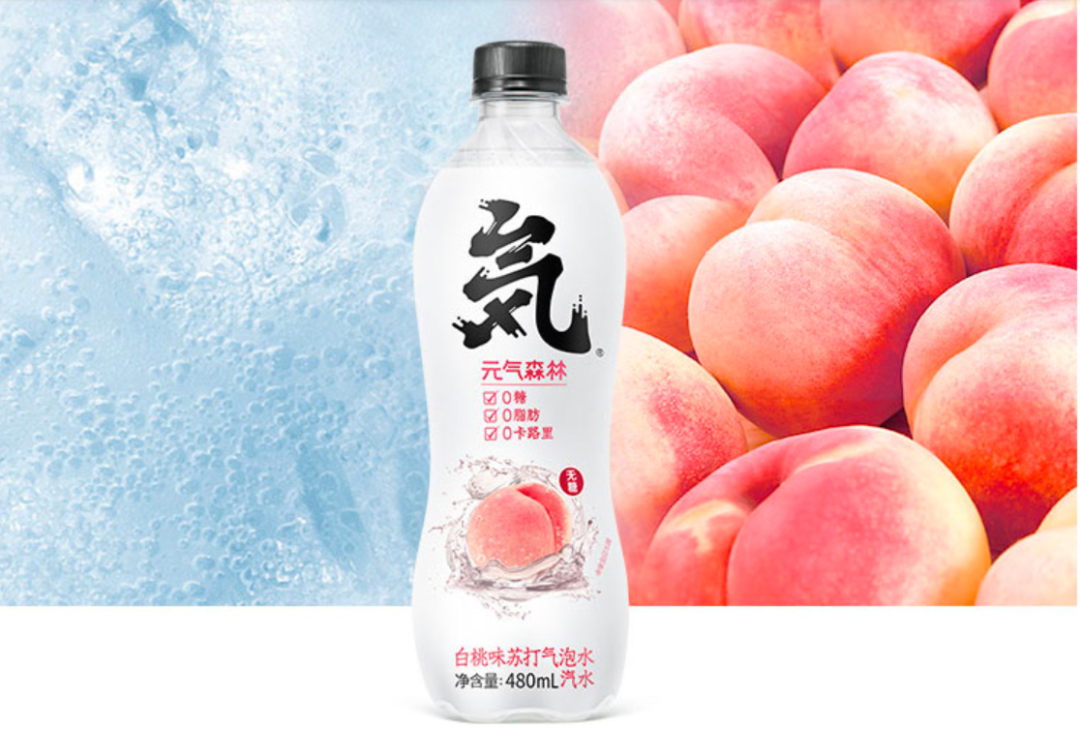
元气森林包装上凸显了“気”字
提到元气森林,你可能记不得包装图案的细节,但一定记得住“气”下面的“×”;提到可口可乐,它飘逸的花体“Coca Cola”或“可口可乐”字体一定给你留下深刻印象。这些产品的字体设计作为包装的一部分,除了审美价值,也成为品牌商业资产的一部分。
一个经典、爆款产品想给消费者留下深刻印象,除了“你爱我我爱你,蜜雪冰城甜蜜蜜”的广告旋律洗脑、除了明星爱豆的代言助力,为什么包装字体这个经常被忽略的元素也很重要?如何打造产品包装的“爆款高分字体”?合适的字体能为品牌会让食品/饮料看起来更好吃/好喝吗?
FBIF2021食品饮料创新论坛创新包装分论坛上,屹涛创意设计创始人陈嵘对字体的解读让我们意识到字体对包装的意义。今天,我们再来聊一聊,食品包装字体的那些事儿。
源头:历史的沉淀赋予设计的沃土
汉字的演变史十分漫长,长到可以拍出一部纪录片。从最早的甲骨文,到后来的隶书、章草、楷书、宋体……
每一种字体都有自己的风格,刻画着所属时代的烙印。书法的意义,已经远超出了字体含义的本身,它们笔画的蜿蜒曲折与肆意搭配,错综复杂出一种艺术、一种文化。
中西方字体
哪怕是在国外,从哥德体到罗马体,从意大利体到现代字体,也都历久弥新成就一个个经典。
当不同地域民族字体的演变史可以拍成一部纪录片,字体的价值以及当中的商业价值被设计家们关注。
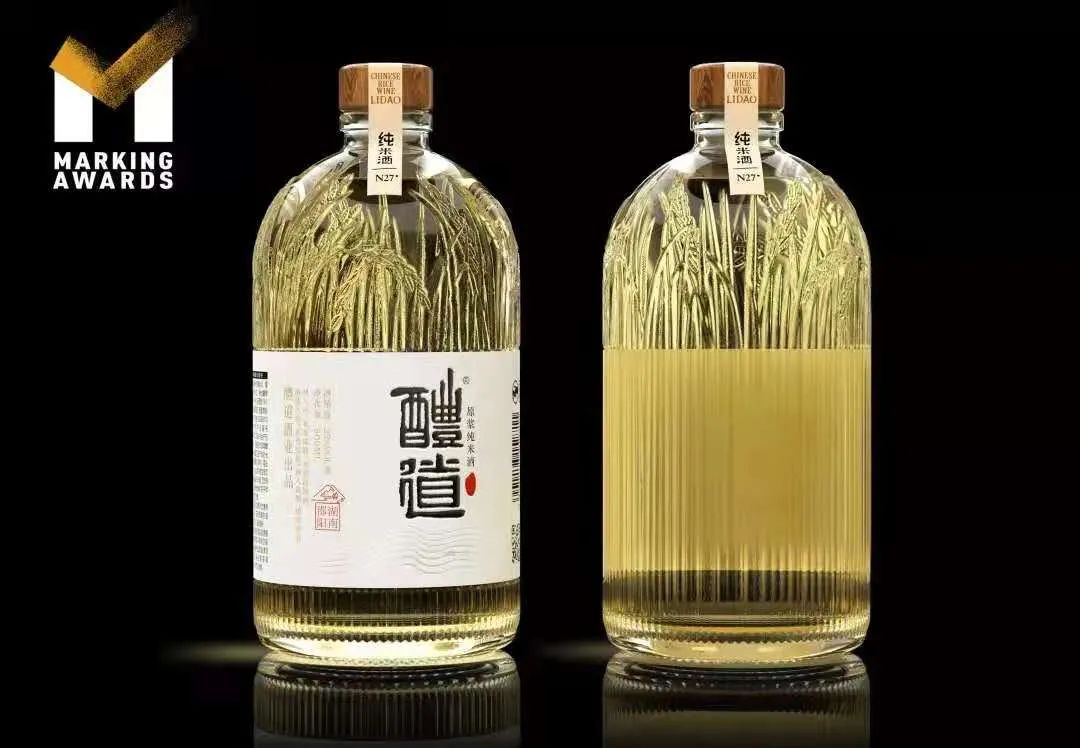
醴道米酒品牌字体选用繁体突出中国特色
尽管火星文、缩写网络流行,但不少品牌还是选择了古体字或者仿古字体。在如今的饮料食品包装上,很多设计依然取自上述的字库。各式各样的字体,成为品牌、logo、口号背后最基础的组成元素。
Dan Shearin设计的Hotel Tango系列烈酒
找到了字体的“库”后,也仅仅意味着一款酒品、一种零食包装的字体设计的开始。就像你从上百种发色中和Tony老师确认了一种发色后,才是染发过程的刚刚起步。
怎样把字库里的字变成品牌包装字体、甚至成为消费者视觉的一种辨识反应?
间距&方向:字体设计的两大玄机
1、间距:“以假乱真”的整齐
请看下图的WonderLab的品牌示例,你认为他们排列整齐吗?
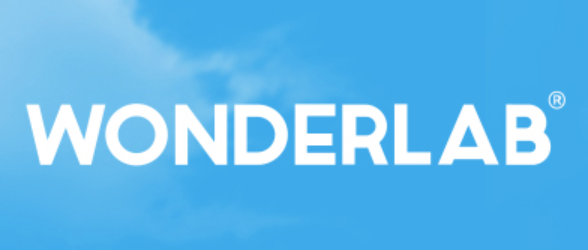
WonderLab
我们看到整齐的一排文字,他们的字间距真的一致吗?答案并不是肯定的。
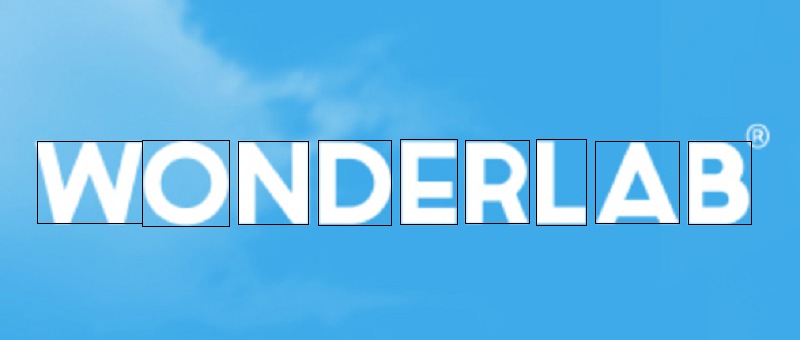
WonderLab字体分割
我们不妨将上图的每个字母所占用的空间框起来,这时你发现了什么?没错,每个字母之间的间距并不如你想象中的一致,而是经过了精心的微调,是”以假乱真“的整齐。
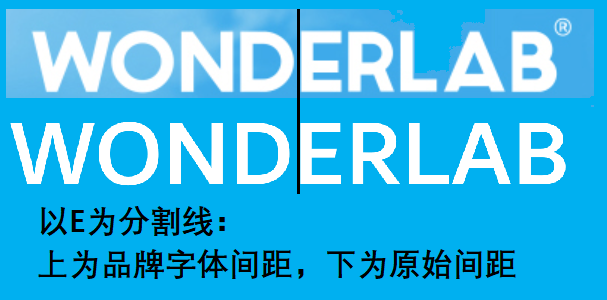
WonderLab品牌字体与原始字体间距对比
甚至当真正整齐的WONDERLAB放出来时,你会觉得它有一点点“零散”,显得标准化甚至略带一丝死板。
你还可以怎样感知间距变化造就的美感呢?旋转或者翻转。
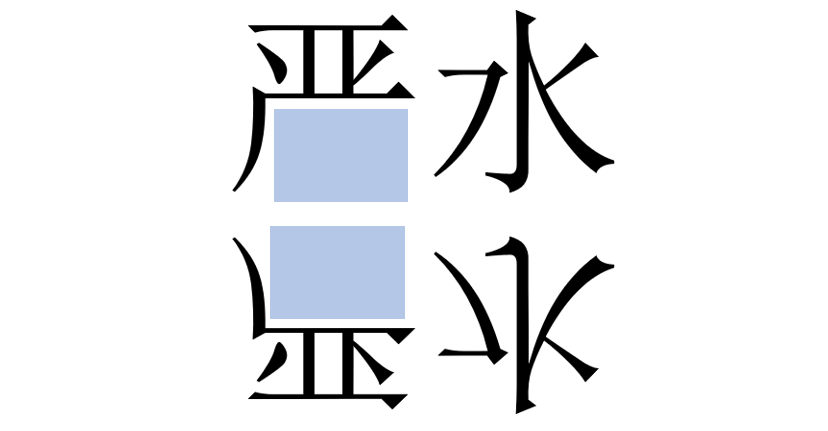
将”严水“二字进行上下对称翻转
可能在大面积的宋体当中,这样的空白没有那么显眼,但是单独的两个字放在一起的时候,通过上下翻转,你可能已经发现了”严“字下方的空白略显突兀。
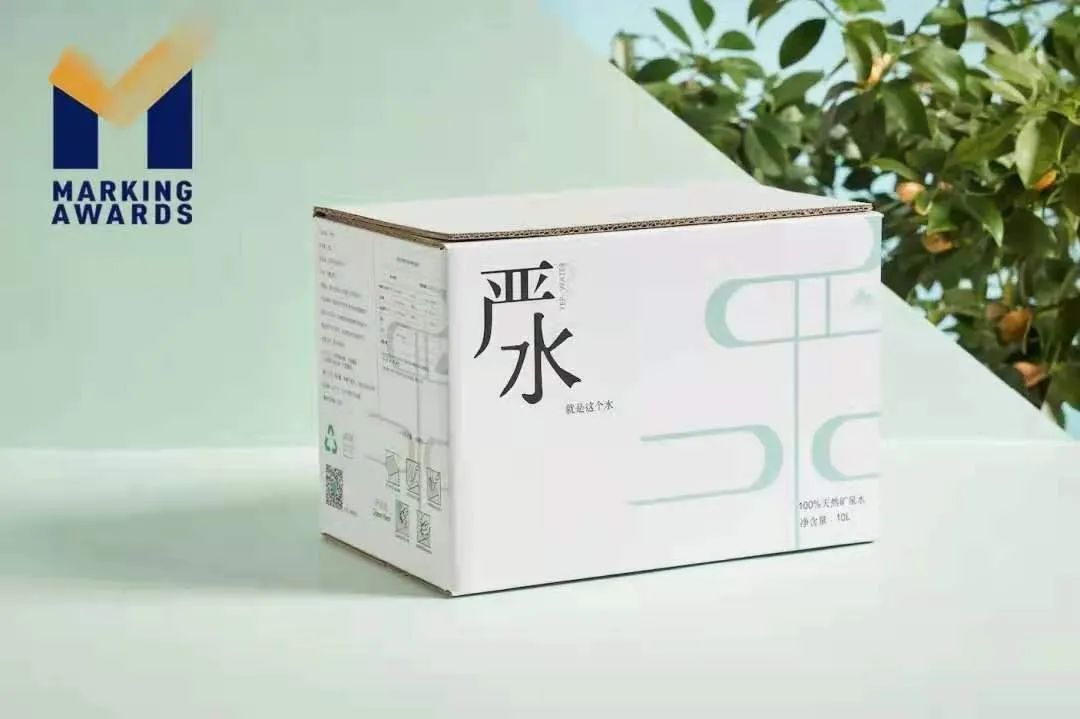
严水产品图上品牌名示意
因此,在天然矿泉水品牌“严水”的包装案例中,其采用的缩进就不再是原始意义上字体之间的间距,而是大胆的将水字向左下方位移(如上图),以实现视觉上空白占比的和谐。
通过改变字体之间的相对位置,大胆地进行位移,可以使产品包装的视觉效果上收获到新的体验。这样的案例并不在少数。
元气森林包装上凸显了“気”字
元气森林将“気”字的字号调大甚至单独放出,与下方的”元气森林“小字紧贴,在突出产品为气泡水的属性的同时,也引导消费者关注到这款气泡水的品牌”元气森林“。
2、方向:左右or上下?
确定好字体之间的间距后,下一个设计的关键便是字体的排列方向。从左到右还是从上到下,并没有对错之分,一切以产品的总体效果为目标。
比如,同样是矿泉水,不同的品牌在排列品牌的字体时却有不同的做法。
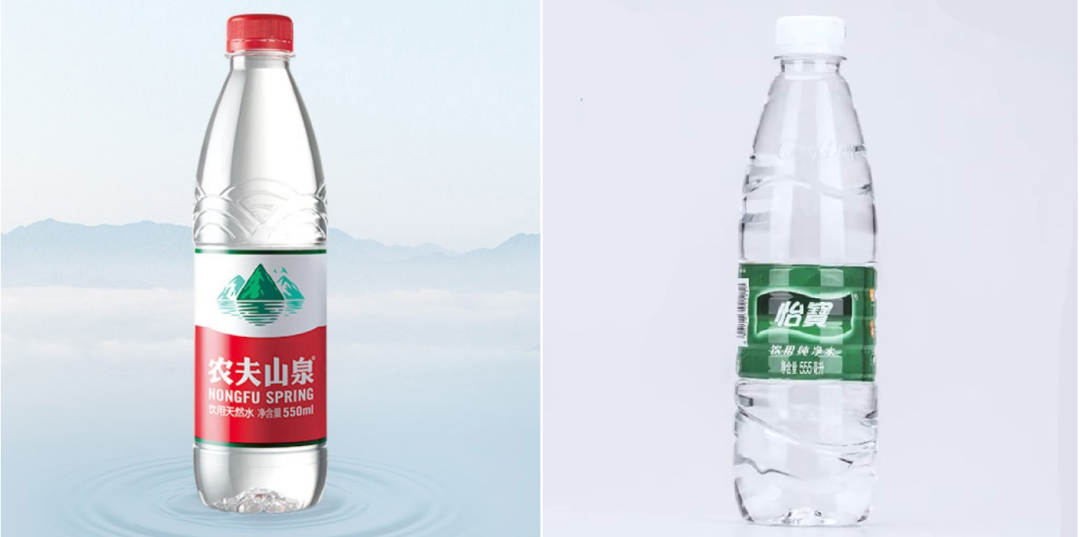
农夫山泉、怡宝
左右型典型代表有农夫山泉和怡宝。
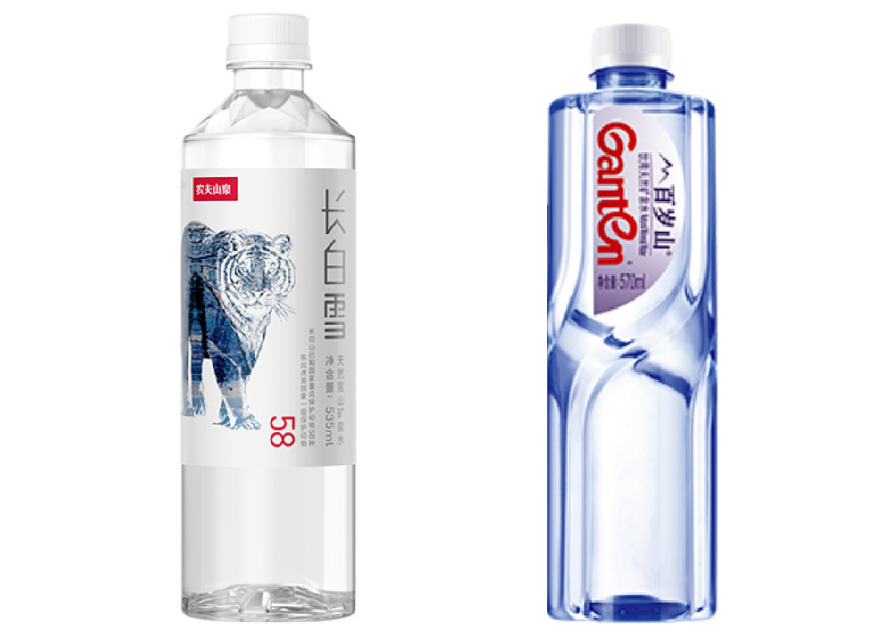
长白雪、百岁山
上下型的代表则有长白雪和百岁山。
字体的排列选择,与瓶身的整体造型有密不可分的关系。左右型的字体其瓶身更加圆润,整体上成下矩形上圆锥的造型,这样的造型将消费者的视觉集中在瓶身的下半部分,此时选择将字体横向放置能够更加收住消费者的视线。上下型的字体排列其瓶身则更加”有棱有角“,相对于前者,消费者的视线会上移,此时将品牌/产品名称竖着排列,并搭配图案(如长白雪瓶身上的虎),能够起到充分利用瓶身空间最大限度呈现品牌/产品想要展现给消费者的内容。
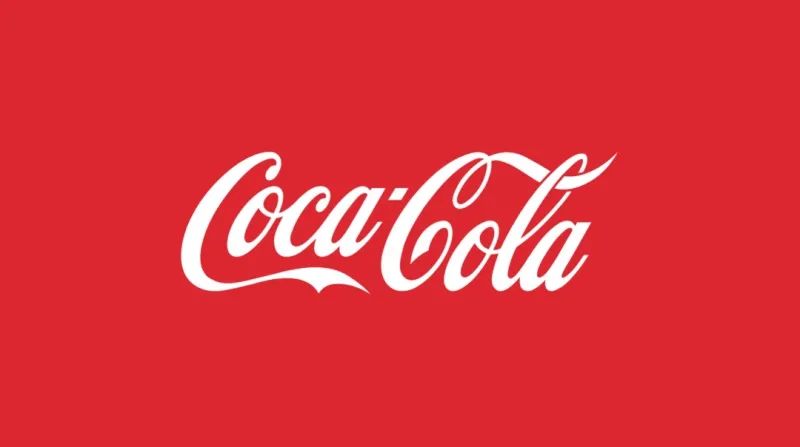
Coca Cola
另一个字体排列需要考虑的因素就是品牌、产品本身名字的长度。比如Coca Cola,8个字母进行排列时,选择横向放置显然更加明智。
让包装图案与字体相辅相成
B’S BEES
尽管有剑走偏锋将整个产品包装上布满产品名字的产品,但更多情形下,包装字体的设计还需要与包装上的其他图案相辅相成,实现美观度、品牌形象和使用效果三方面的理想效果。
QQ星揉揉小肚子酸奶
以QQ星揉揉小肚子酸奶这款为例,瓶身整体被设计为小企鹅揉肚子的造型,因而“揉揉小肚子”5个字选用了可爱软糯糯的字体,并且放置角度也和小肚子的造型相符合,让产品体现出肠道通畅、健康简单的舒适感。若将这5个字换成宋体(如图所示),甚至觉得揉肚子越揉越疼!因而,字体的选用和摆放的角度对于产品呈现的美观度有着不可忽视的作用。
三顿半速溶咖啡图片来源:三顿半天猫旗舰店
品牌形象的方面,我们以三顿半咖啡为例子。三顿半的产品理念有“尝鲜无负担”“3秒溶解于冰水”,品牌也一直在做产品迷你小罐的回收再利用。这样的品牌定位让品牌在选择包装字体的方面也趋于简约、直观的设计——用数字代替文字。数字越小,风味越突出,果酸也会相对明显;数字越大,则越厚实和浓苦,3号和4号相对均衡。
如此一来,通过极简的数字以较大的面积(字号)占据整个包装的面积,不仅方便了老顾客的选择和比较,也能够吸引到新顾客的目光。久而久之,“数字咖啡”也成为三顿半咖啡的特色之一。
字体的使用效果同样不可忽视。字体的设计不仅仅考虑消费者购买的场景,同时也考虑到宣传传播的情形。比如远观一排货架,将琳琅满目的饮料进行模糊,你依然可以识别出Coca Cola,这就对包装字体的辨识性提出了要求。再比如你看的综艺、电视剧时,品牌冠名播出或者产品的广告植入,也是从使用效果方面对于字体提出了要求:有限的屏幕尺寸、有限的广告时间内如何让消费者记住?
电视剧《月光变奏曲》中自嗨锅广告植入
超市速食品货架
不同于化妆品购买过程中消费者会拿着眼影盘、保养品仔细端详,购买速食产品时消费者的决策过程相对较短。因而,从五彩斑斓的货架上看,优雅温柔的飘逸字体在速食类产品中少见,加粗膨胀看起来就有饱腹感的字体更受欢迎。
因而考虑到产品总体的美观度、品牌形象实现使用效果,理想字体背后需要反复的打磨。
好的包装字体能带来什么?
一款好的产品包装字体背后的价值可以远远超过名字本身,对于整个品牌的打造乃至是更宏观层面的文化,都有着积极意义。
麦当劳的“M”演变
图片来源:麦当劳中国官网
麦当劳的“M”,以其独特的字体设计成为麦当劳的代表。你可能记不住麦当劳所有的产品,但你一定能记得住这个双拱门。如今,“金拱门”已成为了麦当劳的代名词,也成为了麦当劳品牌中最具象征性的标志。
金黄色的M像是两扇打开的黄金双拱门,带领顾客走向美食与欢乐。这个独特的黄色,在任何气象状况、时间下都有着较高的辨认性,与辅助的红色实现了和谐。一个简单的“M”背后是字体的独特性、辨识性、记忆性效果的大统一。
品牌本身之外,包装字体还传递着民族文化(历史沉淀)甚至是意识形态。
好望水系列产品
好望水,一个定位新草本饮品的品牌,并在产品中引入中医中“食补”的概念。品牌定位本身就具有很鲜明的“中国特色”,提到草本,许多人都会联想到《本草纲目》;提到“食补”,则更是和西方的抗生素形成鲜明对比。于是在产品包装的字体上,好望水也自然而然的选择的中国的书法字体。中国画的风格加上中国字体的书法,搭配整个产品的玻璃瓶身,散发着中国文化的气息,让整个产品成为中国文化本身的传播载体。
包装字体的设计,真不简单。我们能够记住一款产品,其包装的字体也许就在其中发挥着潜移默化的作用。食品饮料包装的字体还可以有更多创意的迸发,给品牌本身、消费者甚至整个社会带来惊喜。